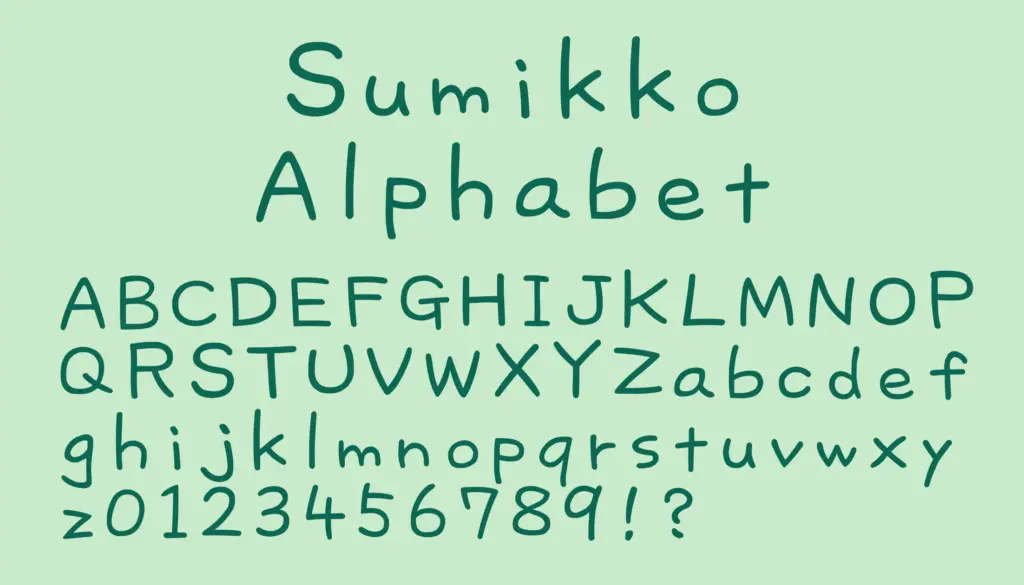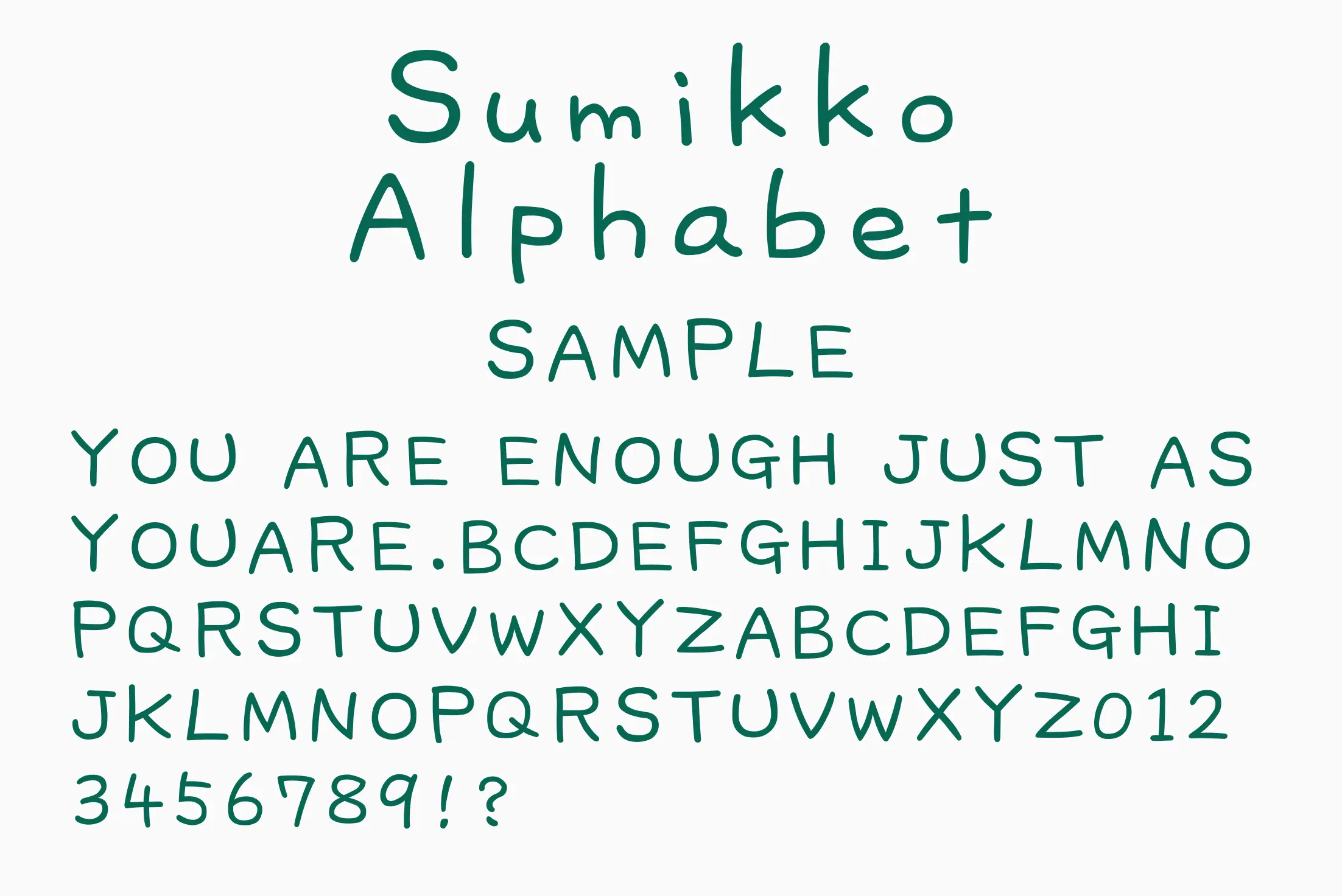
細く丸みを帯びた繊細なアルファベットフォントで、やさしさや温もりを感じさせる書体です。ナチュラルな手書き風で、英語絵本や優しいメッセージカード、ヒーリング系のグラフィックデザインなどにぴったりの雰囲気を持っています。視認性もありながら主張しすぎず、背景やイラストに寄り添うような「そっと添える系フォント」として活躍できます。
Sumikko Alphabet